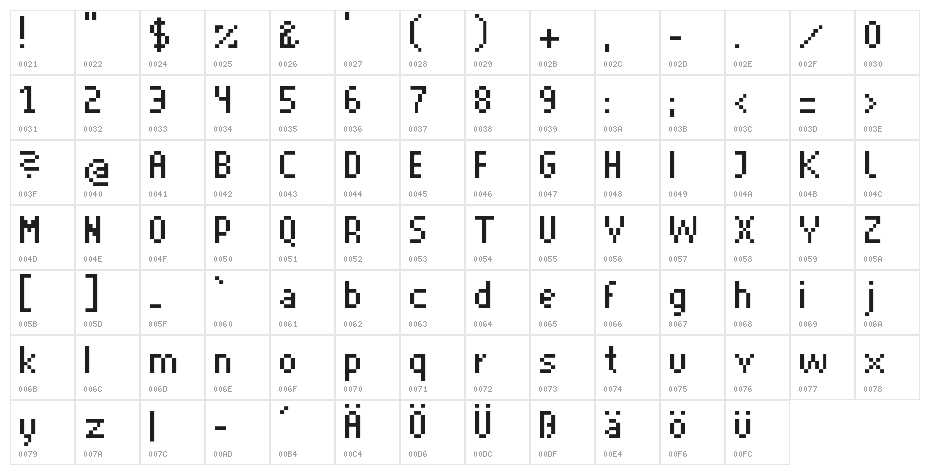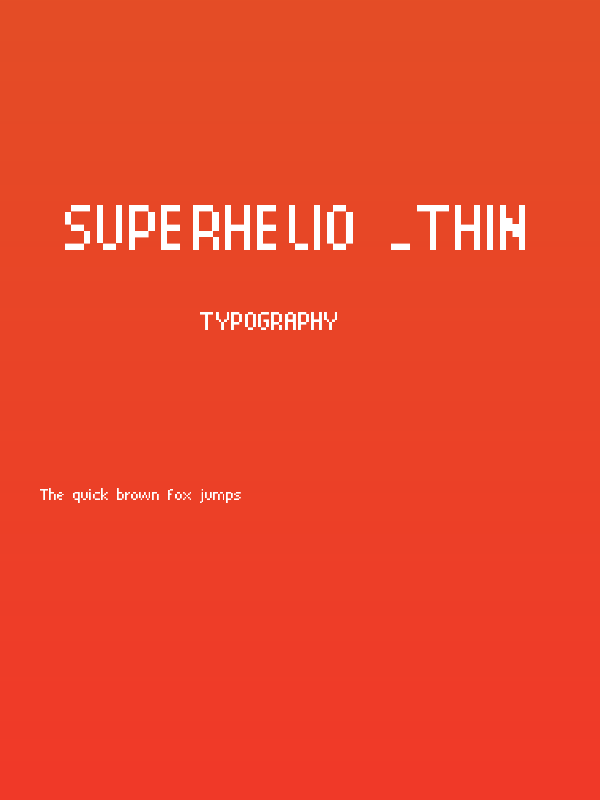
superhelio _thin Font
| Stile generale | Retro, Digital |
| Caso d'uso | Headlines, Logos, Digital displays |
| Progetti proposti | Ideal for retro-themed designs, video game graphics, digital art projects, and any creative work seeking a nostalgic or tech-inspired look. |